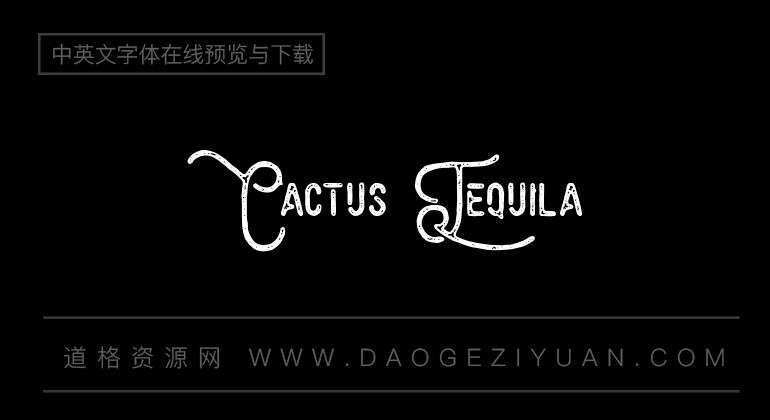
Cactus Tequila 字体是一款拉丁文字体,由设计师Gustavo Dipre创作。字体结构简单,笔画粗细均衡,每个字母都具有独特的外观,具有良好的可读性,适用于任何类型的文字。Cactus Tequila 字体的特点是它的粗细结构,它有一种酒精般的活力,可以让文字脱颖而出。它也具有柔和的外观,可以让文字更有活力,更有吸引力。内容介绍
Cactus Tequila是一款非常不错的手写艺术字体,具有很好的视觉感,适合于文化类的宣传设计、商业类品牌的广告和产品包装设计以及个性化文字排版等较多场景。